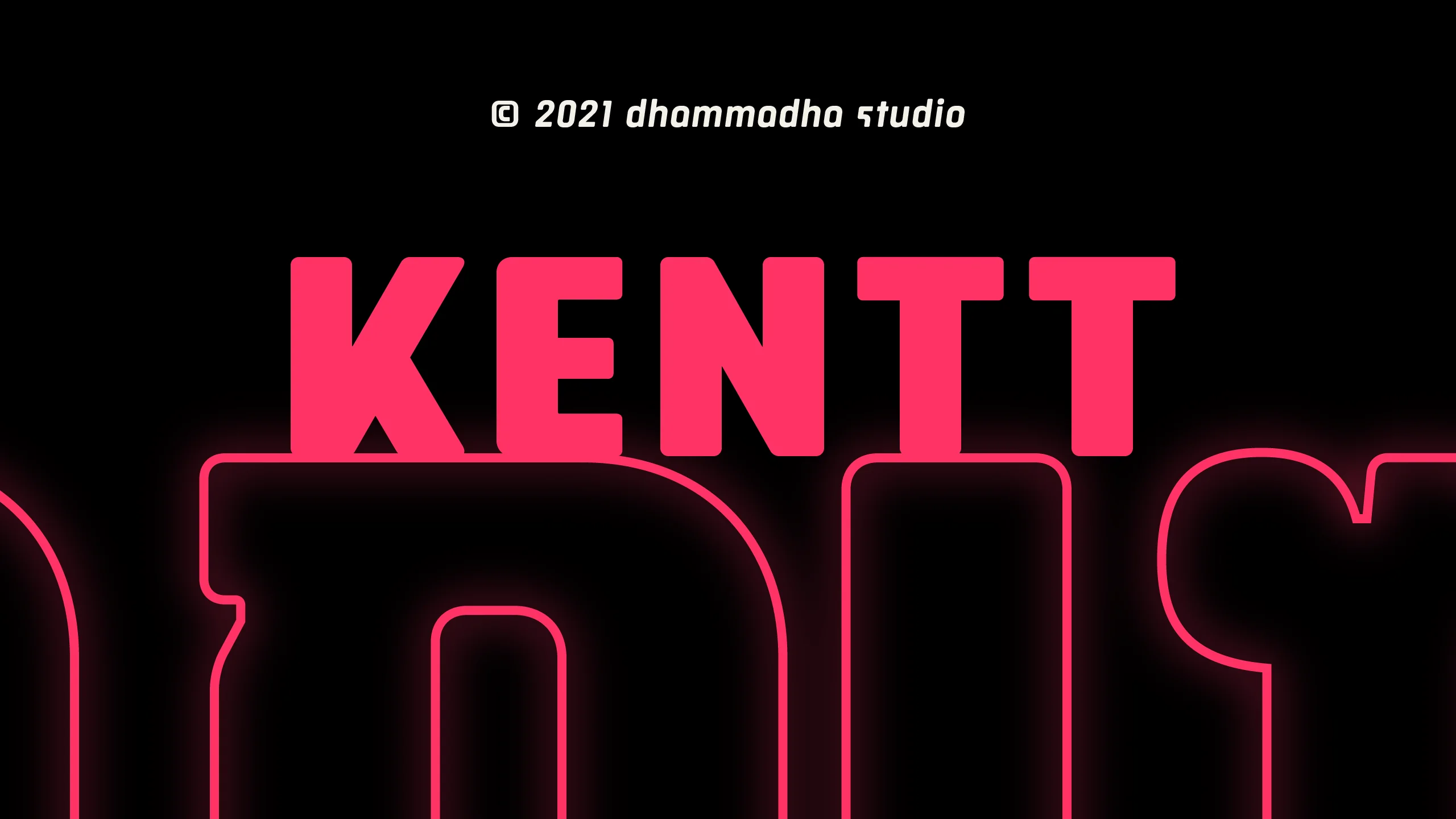
"เกณฑ์ | KENTT" คือชุดอักษรพาดหัวที่สะท้อนถึงความหนักแน่นและความมั่นคงตามแบบฉบับของ DHAMMADHA STUDIO ได้อย่างทรงพลัง แม้จะมีรูปลักษณ์ที่เป็นฟอนต์ Display ขนาดใหญ่ แต่เรายังคงรักษาเอกลักษณ์ที่สำคัญของอักษรไทยอย่าง "หัวตัวอักษร" ไว้อย่างชัดเจน เพื่อช่วยให้การสื่อสารเป็นไปอย่างลื่นไหล ผู้อ่านสามารถเข้าถึงสารได้ง่ายและรวดเร็ว เป็นการผสมผสานระหว่างความร่วมสมัยเข้ากับรากฐานของตัวอักษรไทยได้อย่างลงตัว มอบบุคลิกที่ดูเป็นสากลแต่ยังคงไว้ซึ่งความคุ้นเคยที่น่าเชื่อถือ นอกเหนือจากดีไซน์ที่โดดเด่น เรายังบรรจุเทคโนโลยี OpenType Features ไว้อย่างเต็มรูปแบบเพื่อยกระดับงานออกแบบให้ก้าวไปอีกขั้น ไม่ว่าจะเป็นระบบ Anchor Marking ที่ช่วยจัดการตำแหน่งสระและวรรณยุกต์ให้สวยงามแม่นยำ การจัดช่องไฟแบบ Kerning ที่ละเอียดอ่อน ไปจนถึงชุดอักษรทางเลือก (Stylistic Alternates) สำหรับตัว ก ถ ภ และอักษรอื่นๆ ที่ช่วยสร้าง "สำเนียงใหม่" ในการสื่อสารให้แตกต่างไปจากเดิม พร้อมรองรับการใช้งานที่หลากหลายด้วยชุด Small Caps และ Ligatures "เกณฑ์ | KENTT" จึงไม่ใช่แค่ฟอนต์สำหรับพาดหัว แต่เป็นเครื่องมือสื่อสารที่ช่วยให้ดีไซน์เนอร์สร้างสรรค์ผลงานที่มีเอกลักษณ์และมีชั้นเชิงในระดับสากล